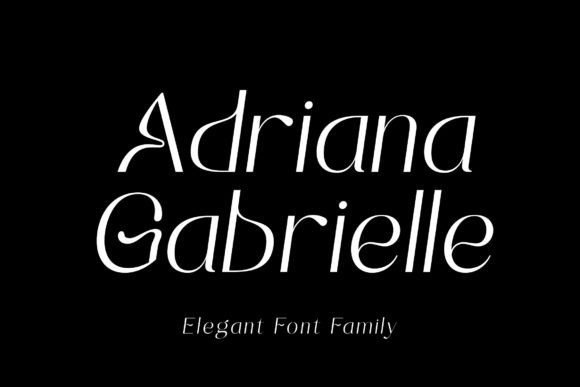
Adrianna Gabrielle
適切なデザイン要素を見つけるのは難しい場合がありますが、Adrianna Gabrielleは作品を即座に引き立てる優れたコレクションを提供します。
POD(オンデマンド印刷)製品、結婚式の招待状、またはソーシャルメディアのグラフィックを作成している場合でも、Adrianna Gabrielleは理想的です。